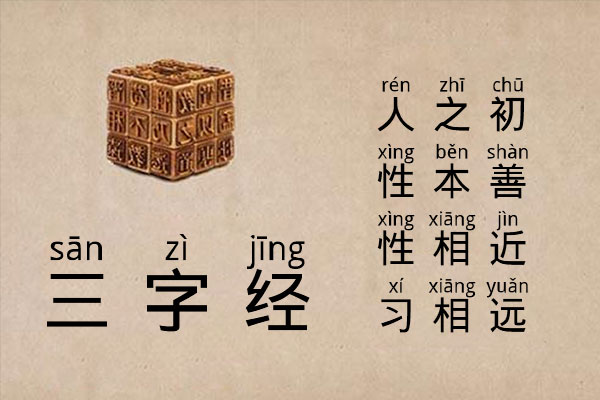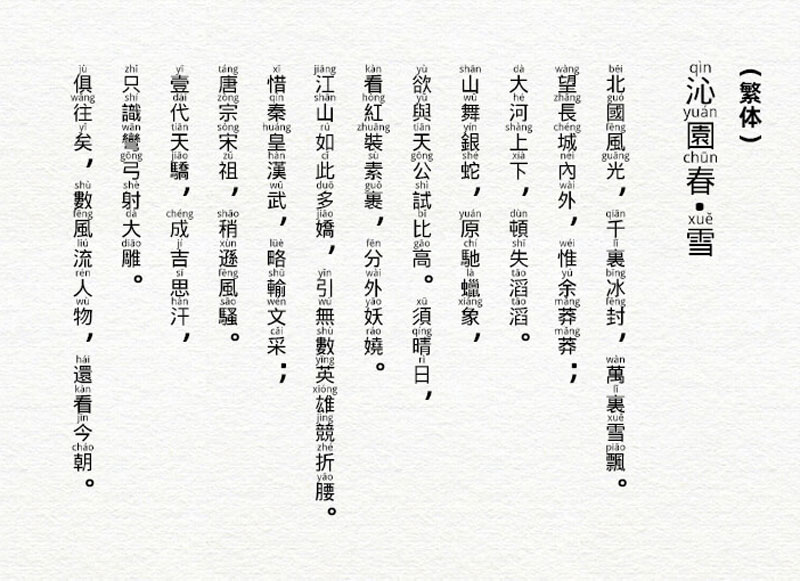
汉字拼音体
汉字拼音体(Hanzi-Pinyin-Font Regular)是一款头上带拼音的字体, 可以帮助学生轻松地学习和阅读汉语的字体。在某些设计场景挺实用的,特别是对教育类的设计比较有用。该字体对简体繁体都比较支持, 详情只展示其中一种,汉字拼音体是遵循CC-BY-SA-4.0授权协议,可以免费用于商业用途、发布,修改,私用等。
汉字拼音体效果预览
汉字拼音体字体效果预览